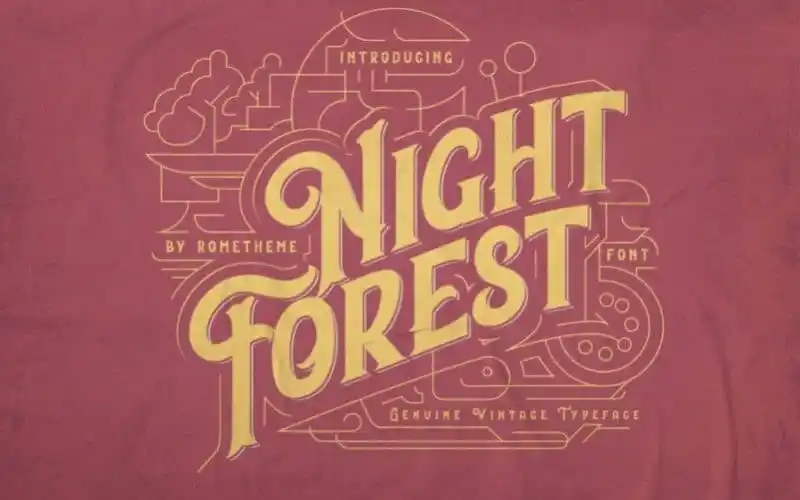
Night Forest Display Font – Fonte Grátis
Night Forest Display Font
A Night Forest Display Font é uma escolha perfeita para quem busca dar mais vida a seus logotipos de maneira moderna e criativa. Inspirada no movimento artístico e arquitetônico, essa fonte consegue trazer um toque vintage que enriquece ainda mais o seu design, especialmente quando usada em projetos de moda e roupas. Suas linhas elegantes, fofas e fashion fazem dela uma escolha perfeita para assinaturas, capas de álbuns, logotipos, marcas de marca, revistas e publicidade. Além disso, a Night Forest Display Font é fácil de usar em projetos variados como redes sociais e anúncios. Seja você um criador de moda ou uma agência gráfica buscando dar vida aos seus projetos, essa fonte tem o que você precisa para trazer seu design ao próximo nível.